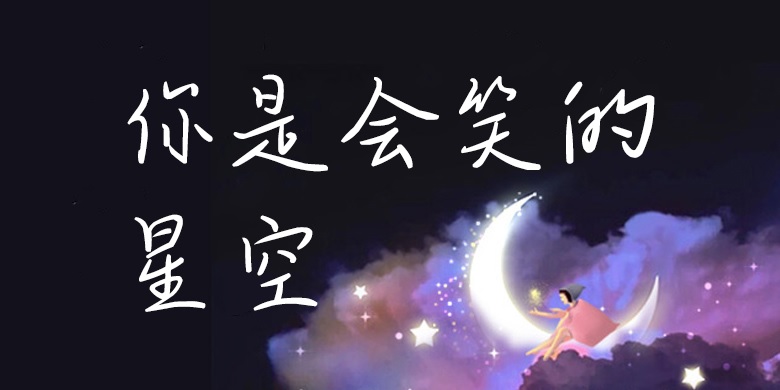
方正手迹-你是会笑的星空
字体品牌: 方正手迹 设计师:俞亦婷 字体分类:常规书写·硬笔 字体属性:精品字 字符集:简繁扩展(GBK) 发布时间: 2020
该字用楷书的笔意去表达行书,但在构字上又多变化,从容不迫而又姿态万千。良好的留白,使得该字具有较好的透气性,因而在阅读舒适性上会有比较清新的体验。适用于文艺类的书刊、品牌广告和产品包装设计,以及社交网络的个性化用字。